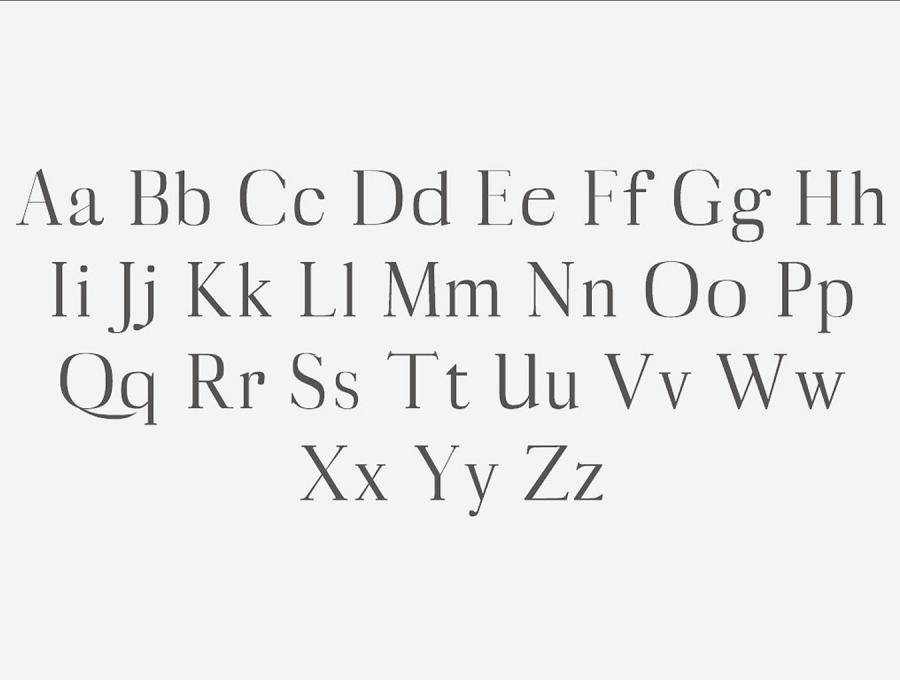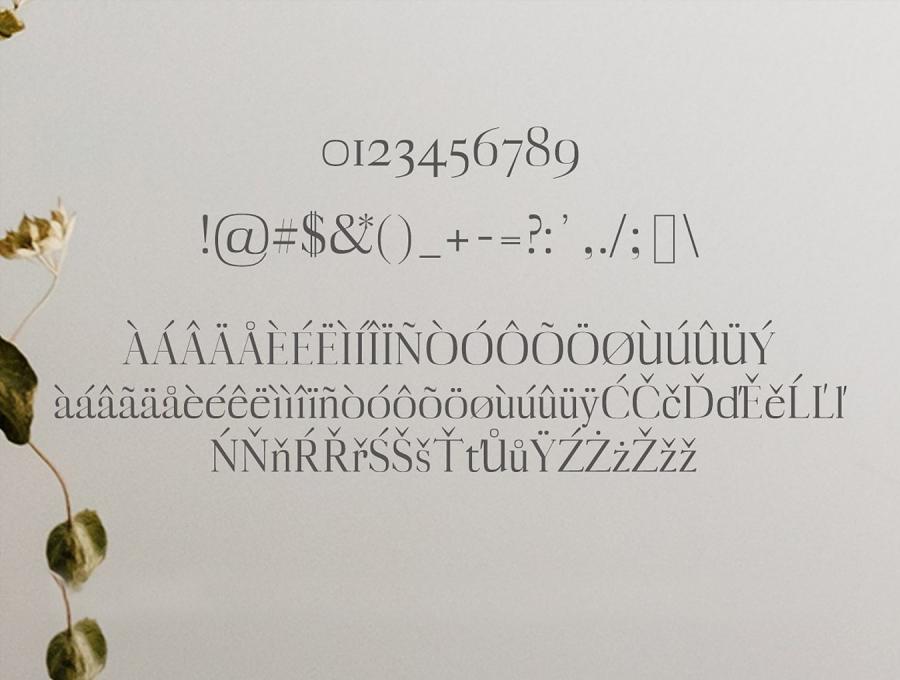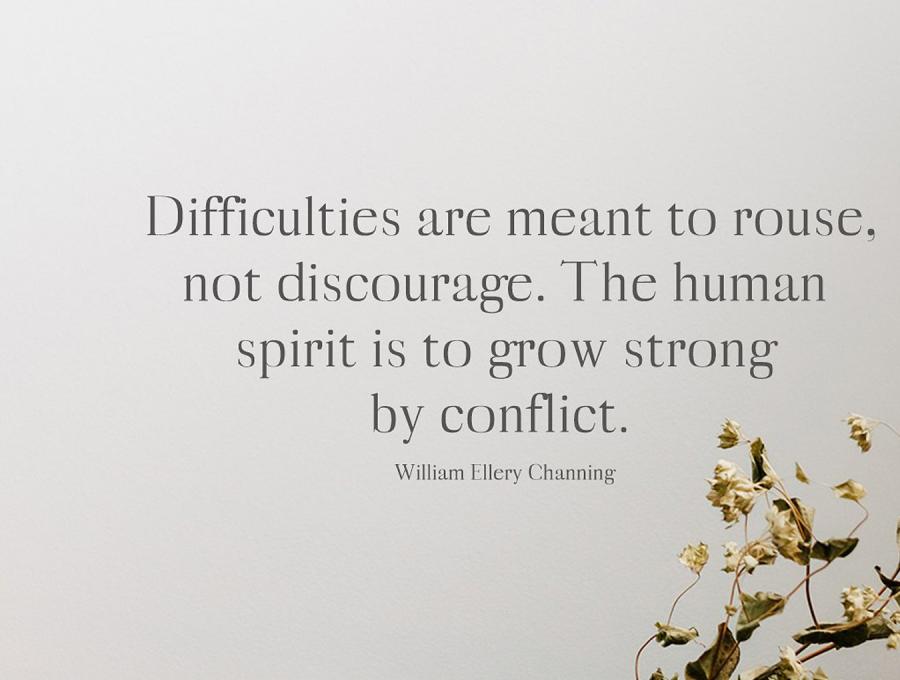
迈伦 英文字体 (Myron Serif Typeface)
Myron Serif Typeface 是一组漂亮的显示字体。 Myron家族包含5个重量,从细到粗。 Myron适用于标题,海报,品牌,包装,演示文稿,短篇小说。 Myron字体特征:大写多语言字母,小写多语言字母数字和标点符号和替代。Myron包含249个字形,是标识,标题,海报或基本字体完美的自定义字体和创意排版。